想來點溫暖可愛的風格,電腦裡的字體看起來卻都很沒人味?你需要的是一些圓滾滾、鈍鈍的、看了就想微笑的可愛字體,會出現在兒童繪本、手作卡片、甜甜餅乾上的那種。
本文會介紹 25+ 款可供免費商業使用,並且一定程度上支援繁體字的可愛字型。
圓體類型的可愛字
這區蒐集的字型看起來較為方正、偏向電腦字體,適合想來點可愛又不能太過頭的時候。
粉圓
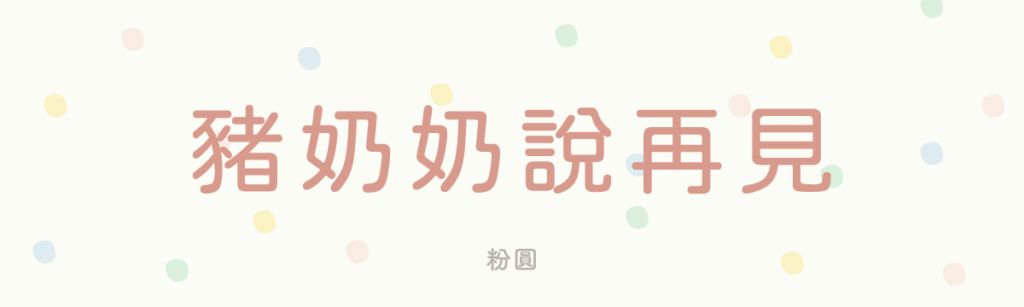
- 不太會缺字 ✅
- 乖巧、工整
字型公司 justfont 曾在金萱字型募資時,承諾為台灣使用者優化一套開源字型作品,以回饋社會。粉圓便是這個承諾的成品。
粉圓是基於 Motoya 公司釋出的 Kosugi Maru 改作而成,justfont 額外設計與調整了近 2,800 個臺灣常用漢字、注音符號與台客原民語羅馬拼音用字,還另外搭配了設計師 Joe Prince 與 Avraham Cornfeld 的開源字體 Varela Round 作為歐文。
源泉圓體
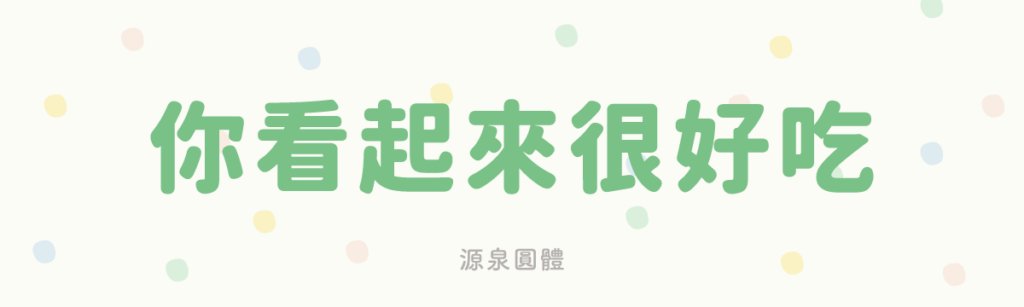
- 幾乎不缺字 💯
- 可愛、趣味
作者 But 有感當時中文圈沒有正統圓體開源字型可用,便以思源黑體為本,調整出一款傳統印刷體風格的圓體。與另一個很有名的開源字型源柔黑體(源柔ゴシック)最大的差別在於,源泉圓體借助程式拔除了所有黑體的腳,看起來更圓潤。
Rounded Mgen+ (ラウンデッド ムゲンプラス)
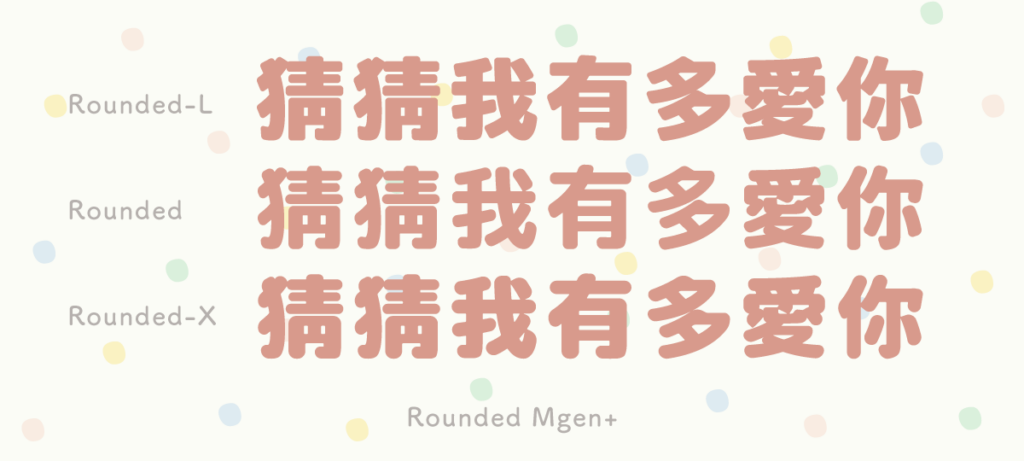
- 不太會缺字 ✅
- 綜藝、誇張
Rounded Mgen+ 是「自家製 Rounded M+」跟「源泉圓體」的混合衍生字型,共有 Rounded-L、Rounded、Rounded-X 三種版本,從 L 到 X 的圓角程度由輕到重,每個版本都有六種粗細。
這套字型支援的漢字範圍高達 1 萬 4,000 多字,遇到缺字的程度大幅降低。解壓縮後你可能會發現怎麼不只一個字型檔,我將不同後綴的說明條列如下:
Zen Maru Gothic(Zen 丸ゴシック)
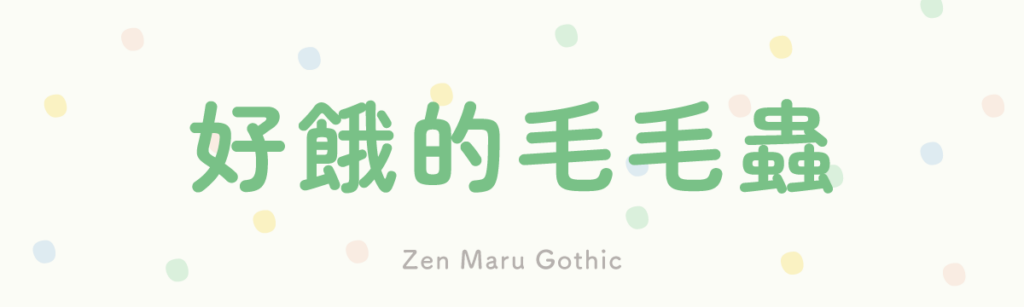
- 容易缺字 ⚠️
- 柔軟、復古
Zen Maru Gothic 比源泉圓體更圓,造型更可愛。如果想找毫無稜角的圓體,不妨考慮用這款字型看看。
Zen Maru Gothic 共有 Light、Regular、Medium、Bold、Black 五款字重,收錄字數不詳,但實測蠻容易缺字喔。製作苦累蛙圓體的 MAX 計畫為 Zen Maru Gothic 補完 4,800 個臺灣常用字,他將補字版本命名為馬路口圓體,目前已釋出體驗版,急用的話可以考慮一下。
蜜瓜體 Mamelon(マメロン)
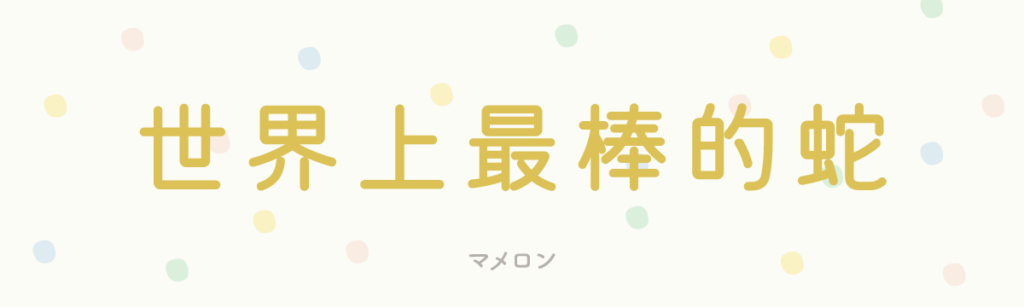
- 容易缺字 ⚠️
- 稚氣、童趣
蜜瓜體 Mamelon(マメロン)曾經以它笨拙、不穩定的造型擄獲無數人的心,然而作者似乎不滿意自己不成熟的作品,在 2020 年將這套字重新改版,重新命名為「マメロン Hi-Regular」並新增四個字重 3、3.5、4、5。收錄字數約有 7,000 多字。
舊版跟新版 Mamelon 其實已經長得完全不像,新版更貼近圓體,造型規矩許多。喜歡舊版的人怎麼辦呢?請往下看。
Humour(ユムール)
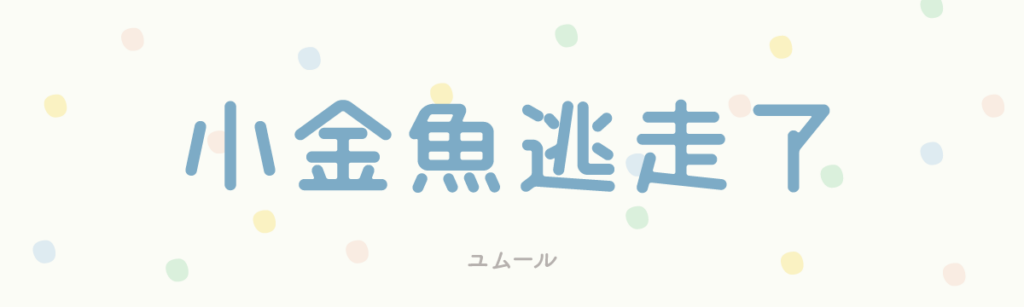
- 容易缺字 ⚠️
- 趣味、活潑
Humour(ユムール)是為了那些懷念舊版蜜瓜體 Mamelon 的人而誕生的。
作者設計新版 Mamelon 的時候,收到一封香港的郵件,內容是「新版的很時尚,舊版的很可愛。請把舊版也公開吧」。此外,作者還發現台灣一款 100% 果菜汁飲料的包裝上使用了舊版 Mamelon,讓他萌生了製作這款字體的念頭。
2023 年,Humour 正式推出,融入了舊 Mamelon 的可愛特徵,讓懷念舊字型的人有了救贖。目前 Humour 的收錄字數僅有 3,000 多字,官網上寫 2024 年會增加更多字,但好像沒有實現,請大家積極用下載表達支持。
LINE Seed JP
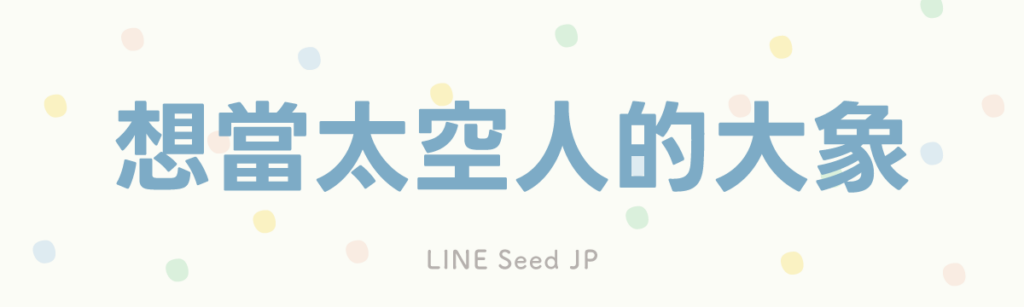
- 容易缺字 ⚠️
- 剛中帶柔
LINE Seed JP 是 LINE 推出的企業字型,開放給大眾免費下載使用。同系列還有英文、韓文、泰文版,不過支援中文(漢字)的只有日本(JP)版,一共有 Thin、Regular、Bold、Extrabold 四種粗細可下載。
設計團隊將 LINE 標誌裡的圓角元素應用到字型中,為 LINE Seed JP 增添了柔和感。收錄字數不詳,實測常用字如「你」、「嗎」還是會缺,製作字數應該不是很完整。
連皮吃奇異果字(キウイ皮ごと齧る)
- 容易缺字 ⚠️
- 厚重、誇張
名字很讓人震撼的連皮吃奇異果字(キウイ皮ごと齧る)改作自上面的 LINE Seed JP,作者重新製作了特粗(ExtraBold)字重的圓角,讓文字看起來更圓潤、可愛。
由於重新製作圓角的過程繁複,目前這款字的收錄字數只有 3,000 多字,日常排版仍有可能缺字。
手寫風的可愛字
內海字體
- 幾乎不缺字 💯
- 稚氣、誠實
內海字體基於日本的瀨戶字體改作而成,有點呆呆的風格相當討喜。
一樣從瀨戶字體衍生的字型還有小賴字體(補齊簡體字)、cjkFonts 全瀨體(機器學習造字)等,作者 MAX 將他們的部份字符併入內海字體,目前內海字體一共有 4 萬 7,417 個字,是這系列衍生字型中最多字數的。
內海字體共有 ExtraLight、Light、Regular、SemiBold、Bold 五種字重,不過因為 Regular 以外的字重都是機器學習產生,可能會有筆畫消失或重疊的問題,使用時要特別注意。
Honya 字 Re(ほにゃ字 Re)
- 容易缺字 ⚠️
- 乖巧、可愛
Honya 字 Re(ほにゃ字 Re)有種盡力寫得工整、但還是有點歪扭的笨拙感。收錄字數包含 JIS 第一・第二水準漢字,約 7,000 多字。
空白筆記本體(じゆうちょうフォント)
- 容易缺字 ⚠️
- 厚重、溫暖
像是簽字筆的字跡,字形穩重,有種可以信賴的感覺。收錄漢字數約 6,900 字。
棗文字(なつめもじ)